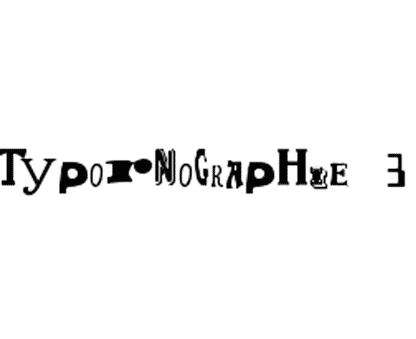
La typographie “anthropophage” et-rotic ne date pas d’aujourd’hui. Même Massin s’y est intéressé en son temps. Geoffroy Tory dans son Champ Fleury nous donne déjà les prépuces de ce style et Picasso s’est donné à cœur joie dans ses dessins pornographiques. Une vraie bouffée d’air dans un monde de brute. En tous cas un grand merci à Laurent pour cette récréation entre deux érections, pardon élections, ma langue à fourchu. Via le site de la Gazette endocrinienne .